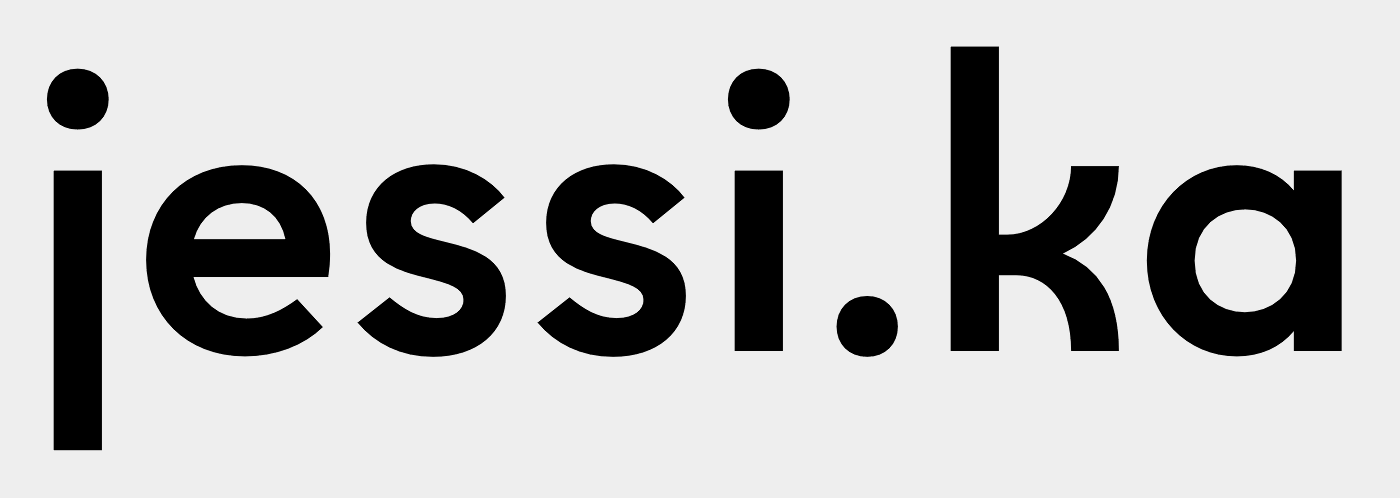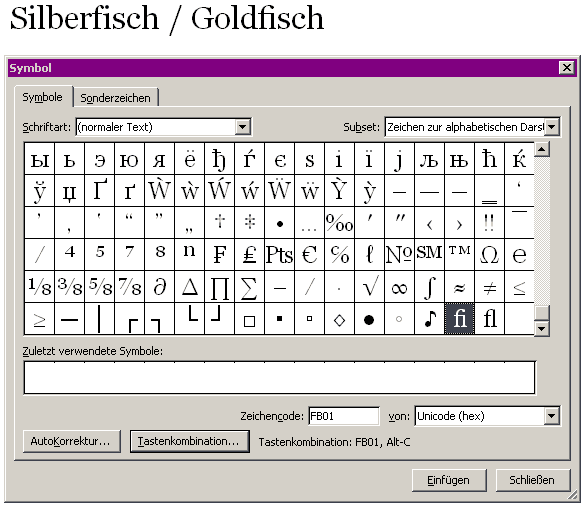
Passende Schrift gesucht!
ich verzweifle schön langsam an meiner eigenen Logoentwicklung... Ich brauche dringen ein paar hilfreiche Tipps!
Ich arbeite unter meinem Namen als Fotografien. Den Bildteil von meinem neuen Logo habe ich inzwischen zu meiner eigenen Zufriedenheit (und meiner eigenen Verwunderung!) endlich fertiggestelltt. Dabei handelt es sich um ein sehr schlichtes rundes Element (nur Konturen), in dem (als Linien stilisiert) meine Initialen stehen.
Jetzt suche ich nach passenden Schriften: Ich stelle mir einen eher schlichten Auftritt vor. Meinen Namen möchte ich gerne in einer ganz simplen Schrift setzen (aktueller Stand der Ermittlungen: https://www.myfonts.com/fonts/radomir-tinkov/gilroy/light/), den Zusatz Fotografie möglicherweise in einer Serifen-Schrift. Beim Wort Fotografie bin ich jetzt schon oft gestolpert, da das f und das i am Ende irgendwie kollidieren (das f verdeckt den i-Punkt dann ganz doof).
Die Kombination der beiden Schriften im Anhang gefällt mir auch sehr gut. Weiß jemand zufällig um welche Schriften es sich dabei handelt?
jessi.ka
Beim Wort Fotografie bin ich jetzt schon oft gestolpert, da das f und das i am Ende irgendwie kollidieren (das f verdeckt den i-Punkt dann ganz doof
Das ist eine fi-Ligatur und Experten finden die im Allgemeinen total toll ;)
Was hälst du von der Quinoa?
Hilfreich wäre es auch, Dein Logo zu sehen, damit die Experten die Bildsprache sehen können.
Auch wäre es sinnvoll zu wissen, welche Software du verwendest. Wenn nämlich f und i nur doof kollidieren, statt das eine richtige, als solche gestaltete Ligatur gezeigt wird, oder speziell für solche Kollisionsprobleme gestaltete Einzelbuchstaben, bedeutet dies, das die von dir verwendete Software OpenType-Funktionen nicht unterstützt, und daher nur die Grundbuchstaben verwendet werden. also statt fi dann f‌i gezeigt wird, was in vielen Schriften wirklich recht doof aneinander stößt.
Und zur Illustration hier noch ein paar Bilder vom Unterschied. Links (zu vermeidende) Kollision, rechts (Kollision vermeidende) Ligatur
Für die Ligaturen fi, fl und soweit in der verwendeten Schriftart vorhanden auch ffi und ffl benötigt man nicht unbedingt ein Programm welches Opentype-Funktionen nutzen kann. Unten habe ich z.B. in Word 2003 bei „Goldfisch“, gesetzt in der Georgia“, eine fi-Ligatur manuell eingefügt. In der Word-Symbolleiste sind die Ligaturen in der Einstellung „Unicode (hex)“ i.A. ganz unten.
Nachteil dieser Methode ist allerdings, daß man bei der Textsuche ein so manipuliertes Wort nicht findet und auch die Rechtschreibkorrektur meckert. Bei der Gestaltung eines Logos dürfte dies aber nicht relevant sein.
Hex  Dezimal Zeichen
fi  FB01 64257   fi
fl  FB02 64258   fl
ffi FB03 64259   ffi
ffl FB04 64260   ffl
Tabelle der in Unicode vorhandenen Standard-Ligaturen
Klar geht das¹, aber ich bekomme ein bisschen Bauchschmerzen dabei, Ligaturneulingen solche Hacks zu erklären. Diese Unicodeligaturen sind uralter Ballast und verursachen sehr viel mehr Probleme als sie lösen. Besser man gewöhnt sich gar nicht erst an sie zu benutzen.
:tuschel: und so habe ich meine obigen Beispielbilder auch produziert, da die Bibliotheken, die meinen Schriftmustergenerator antreiben, partout kein Opentype können :cry:
Nun ja, das stimmt schon, aber leider hat man es noch immer mit Softwareentwicklern zu tun, die meinen, ihre Programme würden ja prima OpenType-Schriften unterstützen, nur weil man aoch Schriftarten mit der Dateierweiterung .otf verwenden kann.
Ich hatte auch ein längeres Gespräch mit einem Softwareentwickler, der nicht die geringste Ahnung von dem hatte, welche Zauberei man mit OpenType-Features anstellen kann, und dann hat es ihm ziemliche Mühe gemacht, zumindest eine noch ziemlich fehlerhafte Bibliothek zu finden, die wenigstens calt und liga einigermaßen unterstützt - wobei man dann auch noch in die Metadaten seiner Fonts eigentlich falsche Werte eintragen muss, damit die Scxhrift auch funktioniert.
lieben Dank schonmal für die zahlreichen, hilfreichen Antworten... da hab ich mich ja ganz schön geoutet, das ich von Ligaturen so überhaupt keine Ahnung habe! :-? Da klingelt wirklich nur ganz weit hinten ziemlich leise was bei mir....
Zum gestalten verwende ich Indesign, da weiß ich auch das man ein Häckchen für Ligaturen setzen kann. Aber aktuell bin ich ja noch auf der Suche nach der richtigen Schrift und habe mir halt nur in der Vorschau diverser Schriften-Websiten wie linotype oder myfonts die Schriften angeschaut. Wenn das da dann so dargestellt wird, als ob die Zeichen kollidieren, kann die Schrift dann keine Ligaturen? (Bitte entschuldigt, falls die Frage total doof ist!)
Übrigens hat Þorsten eben gerade noch einen Fehler in der OpenType Programmierung für dieses /j gefunden; ich werde die Korrektur sobald wie möglich auf MyFonts verfügbar machen.
Leider ist das CALT-Feature bei den Vorschauen auf MyFonts immer noch nicht implementiert.
Stimmt! War mir noch gar nicht aufgefallen. :-?
Hat zufällig noch jemand einen Tipp, um welche beiden Schriften es sich in dem "die hohe Kunst" Screenshot handelt?